Ligatur
Eine Ligatur ist in der Typografie eine typometrische Verbindung zwischen zwei oder drei Buchstaben zu einem eigenständigen Zeichen; Verbundbuchstabe; Buchstabenverbindung; Buchstabenverschmelzung; Haltebogen. Plural Ligaturen.
Die Anwendung von typografischen Ligaturen gehört in den Bereich der Mikrotypografie.
Der Terminus Ligatur entstand in Europa im 18. Jahrhundert. Etymologisch rührt »Ligatur« aus dem mittellateinischen »ligatura« für »Band« zu lateinisch »ligare« für »binden«. Der Begriff Ligatur wird auch in anderen Disziplinen, z.B. der Musik (Notengrafik), in der Medizin oder in der Soziologie, für und in jeweils anderen Zusammenhängen verwendet.
Ligaturen gibt es in allen Schriftgattungen, Hauptschriftgruppen, Schriftarten und Schriftschnitten. Sie unterscheiden sich von nicht verbundenen Buchstaben eines Alphabets in der Regel durch ein geringfügig anderes Aussehen.
Bei physischen Drucktypen für den Bleihandsatz befindet sich eine Ligatur auf einem Schriftkegel bzw. bei OpenType Fonts wird sie als einzelnes Sonderzeichen einer bestimmten Taste zugeordnet bzw. über eine Unicode®-Tabelle adressiert.
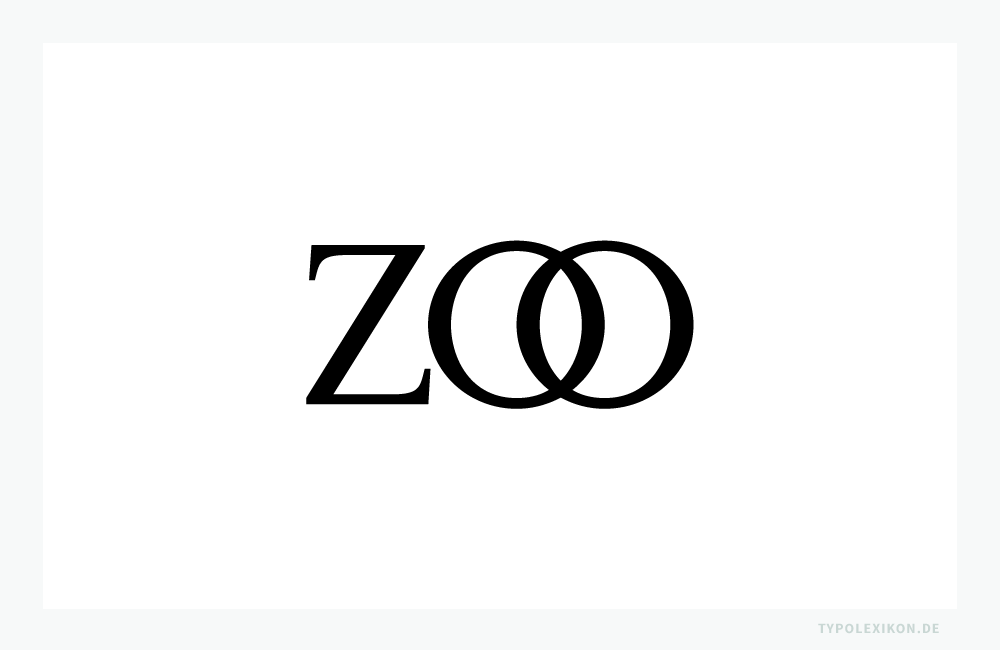
Eine Ligatur verfügt immer über einen natürlichen Breitenlauf bzw. eine feste Normalschriftweite (NSW 0) und kann somit im Sinne des Optischen Schriftweitenausgleichs auch nicht spationiert, unterschnitten oder ausgemittelt werden.
Die Verwendung von Ligaturen ist in keiner europäischen Sprache orthografisch vorgeschrieben. Grundsätzlich sind Ligaturen bei allen Druckschriften und Screen Fonts römischen Ursprungs kein notwendiger Bestandteil des Schriftsystems.
Die deutschen Orthographie kennt – abgesehen vom »ß« (Eszett, Scharfes s), das es heute nur noch in der deutschen Sprache gibt – keine Ligaturen, wobei streng genommen das »ß« in der deutschen Rechtschreibung als Einzelbuchstabe und nicht als Ligatur wahrgenommen wird und ggf. auch durch »ss« bzw. im Majuskelsatz generell durch »SS« ersetzt werden kann (siehe Eszett). 1) 2) 3) 4) 5) 6)
Die Letternarchitektur, die Anzahl von Ligaturen je Schriftart und deren Gebrauch folgt ausschließlich typografischen Regeln, die je nach geschriebener Sprache, Epoche, Schriftart und Schriftsatzsystem voneinander mehr oder weniger stark abweichen. Verbindliche Regeln, wie Ligaturen gegenwärtig im deutschsprachigen Raum gesetzt werden, existierten nicht.
Abgesehen von »&« (et), 7) »§« (signum separationis) 8) »%« (per cento), »@« (engl. at, siehe @-Zeichen) sowie in Deutschland und Österreich »ß« (Eszett, Scharfes s), sind Ligaturen in Tastaturlayouts von Schreibmaschinen, Textverarbeitungssystemen oder Computerterminals nach der Tastaturbelegung 1 der DIN 2137:2012-06 nicht vorgesehen.
Im Segment der Lesetypografie gelten Ligaturen als lesehemmend, da sie nicht mehr den gegenwärtigen Lesegewohnheiten entsprechen. In der Gebrauchstypografie (Akzidenzsatz) bzw. im Grafikdesign werden sie gerne als Zierligaturen verwendet. Innerhalb von Webanwendungen können Ligaturen ggf. zu Performance-, SEO- 9) und Kompatibilitätsproblem führen.
Ligaturen können nur mit professionellen Desktop Publishing Computerprogrammen, beispielsweise InDesign® von Adobe® oder QuarkXpress® von Quark®, und Fonts (z.B. OpenType Fonts) mit Ligaturen in einen Schriftsatz korrekt eingearbeitet werden. In Textverarbeitungsprogrammen, z.B. Microsoft Word® oder Pages von Apple®, können Standardligaturen zwar im Rahmen der OpenType-Technologie automatisch aktiviert, jedoch nicht fachgerecht verwendet werden.
Ursprung und Historie
Die Epigraphik, die Paläografie und die Diplomatik dokumentieren bereits in vorrömischen Alphabeten erste Zeugnisse von Ligaturen und Abbreviaturen (Abkürzungen). 10) Bis zur Spätantike dienten sie dazu, den Zeilenanfang und das Zeilenende optisch auszugleichen (Optischer Randausgleich). Besonderer Ligaturenreichtum ist bei epigraphischen Schriften festzustellen.
In der Kalligraphie erfüllten Ligaturen primär die Aufgabe, schnell und ökonomisch zu schreiben, da u.a. Trägermaterialien wie Pergament bzw. später Papier sehr rar und kostbar waren. Sprachliche Aspekte, beispielsweise die Entwicklung des Konsonanten »w« aus einer Ligatur von zwei »v« bzw. »u« kamen erst später hinzu (11./12. Jahrhundert). Ästhetische Aspekte in der Formgebung und Anwendung erst nach dem Manierismus. Generell ist es sehr schwer festzustellen, ob und ab wann eine Ligatur als originär oder als zusammengesetzt betrachtet werden muss.
In der europäischen Kalligraphie werden Ligaturen spätestens seit dem 1. Jahrhundert – z.B. in Form des Et-Zeichens (lt. »et« für »und«) – genutzt. Zu den ältesten noch angewandten Wortligaturen zählt das Et-Zeichen aus dem Zeichenrepertoire der Tironischen Noten von Marcus Tullius Tiro (um 103–4 v.Chr.), welches auch heute noch in Irland in unveränderter Form genutzt wird.
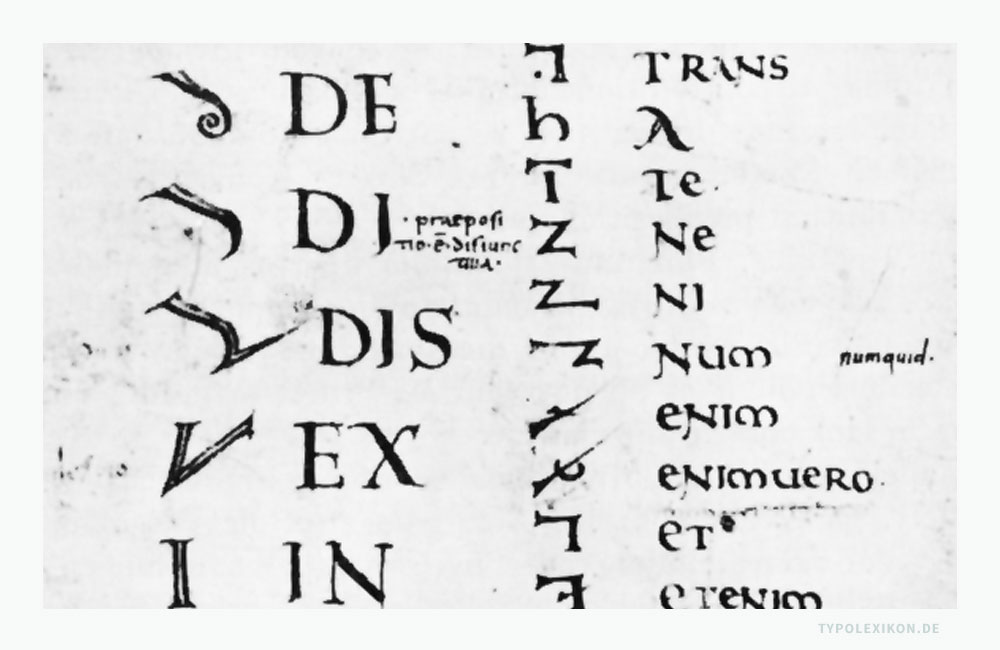
Der Prototypograf Johannes Gutenberg (um 1400–1468) übernahm aus der Kalligraphie die Formgebung von Ligaturen und Abbreviaturen. Beispielsweise entwarf und schnitt er 1460 für den Druck der berühmten Mainzer Erstausgabe des aus dem Jahre 1286 stammenden »Catholicon« – ein in lateinischer Sprache verfaßtes etymologisches Wörterbuch und einer Grammatik zur Bibel – des Dominikanerpaters Johannes Balbus (geboren vermutlich in der ersten Hälfte des 13. Jahrhunderts in Genua, gestorben um 1298) eine »Gotico-Antiqua-Type« (Catholicontype) mit 22 Majuskeln, 103 Minuskeln mit und ohne Abbreviaturen, 81 Ligaturen und vier Sonderzeichen. Insbesondere die Ligaturen nutzte Gutenberg, um in zwei Kolumnen zu jeweils 66 Zeilen platzsparend drucken zu können.
Ligaturen wurden im deutschsprachigen Werksatz von Offizinen rund 500 Jahre lang bis zum Ende des materiellen Schriftsatzes (Bleisatz) verwendet; in der BRD, Österreich und der Schweiz bis Mitte der 1980er bzw. in der DDR teilweise bis nach der deutschen Wiedervereinigung (1989/1990), u.a. von der Offizin Andersen Nexö in Leipzig. 11)
Ab den 1960er Jahren mit der sukzessiven Einführung des Fotosatzes (optomechanischer Schriftsatz) und dem damit einhergehenden Verzicht der Buch- und Zeitungsverlage auf die Verwendung von typografischen Ligaturen – dies war nun technisch möglich und deutlich günstiger –, veränderten sich auch die Lese- und Betrachtungsgewohnheiten der deutschlesenden Rezipienten.
Spätestens ab Mitte der 1980er Jahre sind typografische Ligaturen in Deutschland, Österreich und der Schweiz nicht mehr gebräuchlich.
Arten von Ligaturen
Bei Druckschriften und Screen Fonts römischen Ursprungs gibt es unterschiedliche Arten von Ligaturen:
- Kaufmannsligaturen, z.B. das Prozentzeichen »%«
- Tonligaturen
– Phonetische Majuskelligaturen, z.B. »Æ«
– Phonetische Minuskelligaturen, z.B. das Eszett »ß« - Typografische Ligaturen
– Minuskelligaturen zweifach, z.B. für »fi«
– Minuskelligaturen dreifach, z.B. für »ffi«
– Majuskelligaturen zweifach, z.B. für »TT«
– Majuskelligaturen dreifach, z.B. für »THE« - Unterschneidungsligaturen (siehe Unterschneiden)
- Wortligaturen, z.B. »&«
Im deutschsprachigen Raum werden heute nur noch die Tonligatur »ß« (Eszett), 12) die Wortligaturen »&« (et) und »§« (signum separationis) 13) sowie die Kaufmannsligaturen (ligatura mercatoris) »%« (per cento) und »@« (engl. at) verwendet.
Im Hochdeutschen ist der Schriftsatz, abgesehen von »ß«, frei von Ligaturen, wobei wie bereits erwähnt, das »ß« aus Sicht der deutschen Orthographie als Sonderzeichen wahrgenommen wird, nicht als Ligatur.
Gründe für die Verwendungen von Ligaturen
Im materiellen Schriftsatz werden Ligaturen aus folgenden Gründen verwendet:
- als Ersatz für manuelle Unterschneidungen, die im Blei- und Holzsatz sehr aufwendig und materialintensiv sind
- als Lesehilfe zur Verdeutlichung von Wortfugen
- als platzsparende Abbreviaturen
- als Zierligaturen (Schmuckligaturen)
- um bei bestimmten Buchstabenkombinationen kritische Vor- und Nachbreiten zu vermeiden, die einen ungleichmäßigen Grauwert zu Lasten der Lesbarkeit und der Ästhetik ergeben könnten
- um die Aussprache eines Lauts zu verändern
- um einen Formsatz zu erzwingen
- um im Werksatz im natürlichen Breitenlauf (Normalschriftweite) platzsparend zu setzen
Und im DTP Desktop Publishing: 14)
- als platzsparende Abbreviaturen
- als Zierligaturen
- bei deutschem Fraktursatz
- um die Aussprache eines Lauts zu verändern
Ligaturen im deutschsprachigen Bleisatz
Grundsätzlich ist festzustellen, dass die Fraktur über 400 Jahre die Buch- und Verkehrsschrift der Deutschen und Österreicher und bis 1941 die offizielle Amtsschrift im Deutschen Reich war. Der deutsche Typograf und Schriftgelehrte Jan Tschichold (1902–1974) bemerkte: 15)
Wie kommt es, dass die alten Antiquaschriften vor der Mitte des 19. Jahrhunderts kein ß enthalten? Es war bis gegen 1800 gar nicht, später nur selten üblich, Deutsch in der Antiqua zu setzten …
Der Gebrauch von Ligaturen im deutschsprachigen Raum konzentriert sich deshalb überwiegend auf die der Gebrochenen Schriften. Daraus ergeben sich – im Vergleich zur Französischen oder Englischen Typografie – eigenständige Gesetzmäßigkeiten in Form, Aussprache und Anwendung von Ligaturen beim Satz Gebrochener Schriften.
Der ausschließliche Gebrauch von Antiqua-Schriften in der deutschen Sprache während des materiellen Schriftsatzes beschränkt sich in Deutschland und Österreich auf rund 40 bis maximal 50 Jahre – von ungefähr Mitte der 1940er bis Ende der 1980er Jahre.
Minuskelligaturen im deutschsprachigen Bleisatz
Minuskelligaturen für Werksatzschriften wurden bzw. werden auf einem Schriftkegel im natürlichen Breitenlauf geschnitten. Bei der Fraktur sind die Zweifachligaturen ch, ck ff, fi, fl, ft, ll, fch, ∫i, ∫∫, ß, ∫t, tt und tz sowie die Dreifachligatur fch geläufig. Sie galten im Fraktursatz als unabdingbar (korrekte Formgebung der Frakturligaturen siehe Abbildung ↓ der Schriftprobe »Wilhelm-Klingspor-Schrift«). Der Typograf Albert Kapr (1918–1995) beschrieb ihre Wichtigkeit folgendermaßen: 16)
Eine Quelle der Schluderei beim Satz gebrochener Schriften ist das Mißachten von Ligaturen, die beim nicht gesperrten Satz unbedingt eingesetzt werden müssen, so tz, ß, ∫i, ∫t, ∫i, ff, fl, fi, ll, ch und ck und gelegentlich noch einige andere.
Bei den Antiqua-Schriften waren in Deutschland und Österreich nach dem II. Weltkrieg die Zweifachligaturen für ch, ck, ff, fi, fl, ft, ß und tz sowie selten Dreifachligaturen für ffi und ffl gebräuchlich.
Majuskelligaturen im deutschsprachigen Bleisatz
Da bei Gebrochenen Schriften der Versalsatz nicht üblich ist – die Alternative zum Satz in Großbuchstaben war der Sperrsatz–, kennt die »Deutsche Schrift« folglich auch keine Majuskelligaturen, sondern nur Minuskelligaturen. 17) Phonetische Majuskelligaturen, z.B. »Æ«, gab es überwiegend nur für Antiqua-Schriften im Fremdsprachensatz, äußerst selten bei Fraktur-Schriften, so beispielsweise bei der »Peter-Jessen-Schrift« des Offenbacher Typografen Rudolf Koch (1876–1934), die 1931 bei Schriftgießerei der Gebrüder Klingspor in Offenbach am Main erschien.
Die phonetischen Majuskelligaturen »Æ« und »Œ« (bzw. »æ« und »œ«) wurden von deutschen Handschriftsetzern als Französisches Betonungszeichen (Akzentzeichen) für»Ä« und »Ö« verstanden, nicht als typografische Ligaturen. 18)
Regeln für das Setzten von Ligaturen
Verbindliche Regeln, wie Ligaturen im deutschsprachigen Raum gesetzt werden, existierten heute nicht mehr. Allerdings gibt es gewisse Reglements, die sich aus den »Regeln zur Verwendung von Ligaturen im Fraktursatz« in Relation zur deutschen Rechtschreibung des beginnenden 20. Jahrhunderts rekrutieren.
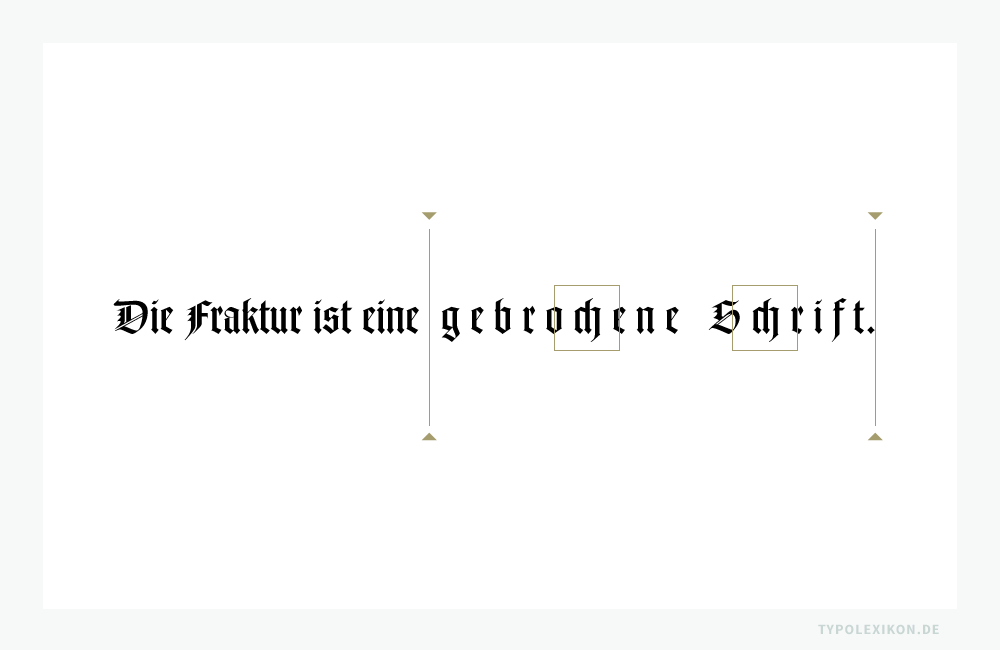
Geläufige Regeln (Auswahl) für den deutschsprachigen Ligaturensatz:
- bei der Spationierung einer Antiqua werden alle Ligaturen aufgelöst
- bei der Worttrennung am Zeilenende werden Ligaturen aufgelöst
- im Sperrsatz einer Fraktur müssen die Ligaturen aufgelöst werden, jedoch nicht ß, tz, ch und ck
- keine Ligaturen für getrennt gesprochenen Buchstaben
- keine Ligaturen im gesperrten Satz
- Ligaturen dürfen am Wortende (Beugungsendungen und Endsilben) nicht getrennt werden, jedoch bei mit einer »i« beginnenden Nachsilben schon
- Ligaturen richten sich nicht nach den Sprachsilben
- Ligaturen sind dort anzuwenden, wo sie die sprachliche Richtigkeit nicht stören
- Ligaturen verbinden keine Wortstämme von Komposita
- Minuskelligaturen im Versalsatz von Antiqua-Schriften sind nicht erlaubt
- ss kann es nicht geben, stattdessen muss eine Ligatur verwendet werden
- treffen drei Buchstaben zusammen, von denen je zwei eine Ligatur bilden können, entscheidet die Silbengrenze
Die Ligatur »Eszett« in der Schweiz
Die Schweiz (und Lichtenstein) bildet in Bezug auf die Ligatur »ß« (Eszett) eine Ausnahme, da deren Kantone zum Ende der 1930er Jahre begannen, das »Scharfe s« in den Primarschulen (Grundschulen) nicht mehr zu lehren. 19) Das althergebrachte Eszett wird seither in der Schweiz mit »ss« aufgelöst, was gemäß der deutschen Orthographie auch in Deutschland und Österreich möglich ist. Offiziell abgeschafft wurde das »ß« in der Schweiz allerdings aber nie.
Ligaturen im digitalen Corporate Publishing
Abgesehen von Ton-, Wort- und Kaufmannsligaturen ist der korrekte Gebrauch von Buchstabenverbindung – z.B. von Bogenligaturen – für den digitalen Mengensatz nicht standardisiert und sehr zeitaufwendig.
Ligaturensatz mit Layout- und Satzprogrammen
Im DTP Desktop Publishing ist es mit professionellen Layout- und Satzprogrammen, beispielsweise InDesign® und Illustrator® von Adobe® oder QuarkXpress® von Quark®, technisch möglich, jegliche Arten von Ligaturen aus einem OpenType Font in einen Schriftsatz einzuarbeiten.
Da professionelle Layout- und Satzprogramme für den internationalen Markt optimiert sind, folgen sie keinen speziellen sprach- und landesspezifischen typografischen Regeln für die Verwendung von Ligaturen. Ein stereotyper Austausch von Buchstabenpaaren (z.B. »fi« oder »ff«) gegen die jeweilig korrespondierenden Standardligaturen ist nach den typografischen Regeln gemeinhin fehlerhaft (siehe obige Regeln für das Setzen von Ligaturen).
Ligaturen bei OpenType Fonts
Seit dem Jahre 1997 ist es durch die OpenType-Fonttechnologie von Adobe® und Microsoft® möglich – ein Font kann technisch betrachtet +/-65.000 Zeichen im Unicode®-Zeichencodierungsstandard umfassen –, Druck- und Screen Fonts mit einer Vielzahl von Ligaturen auszustatten, wobei Unicode® nur für rund 40 Standardligaturen für die Sprachen lateinischen Ursprungs Unterstützung bietet. Das Unicode Consortium lehnt es grundsätzlich ab, weitere Ligaturen in den Unicode® aufzunehmen, da dadurch schwerwiegende Kompatibilitätsprobleme mit bestehenden Zeichenkodierungen entstehen. 20) 21)
Unabhängig davon ist in der digitalen Schriftgestaltung (Type Design) allerdings seit einigen Jahren bei Antiqua-Schriften eine babylonische Vielzahl von Ligaturen zu beobachten, die in ihrer Formvielfalt und Anzahl die der analogen Ära weit übertrifft.
Im Zeichenvorrat (Figurenverzeichnis) eines Fonts, insbesondere von Zierschriften (Decorative), kann es Duzende von fantasievollen Verbundbuchstaben geben. Vereinzelt finden sich bei OTF Fonts auch spezielle Schriftschnitte, deren Zeichenrepertoire ausschließlich aus Ligaturen besteht, beispielsweise die Mrs Eaves Just Ligatures Roman von Zuzana Licko, USA 1995, die u.a. auch Majuskelligaturen für CE, OC, OG, OO, CE, TE THE, TR, TT, TW TY, UR oder VA enthält und den normalen Schriftschnitt der Mrs Eaves ergänzt.
Bei Gebrochenen Schriften in OTF-Formaten dagegen ist das Angebot an Ligaturen sehr begrenzt und für den deutschsprachigen Ligaturensatz in der Regel unvollständig. Darüberhinaus herrscht bei dieser Schriftgattung ein heilloses Tohuwabohu bei der Adressierung (Codierung) der Ligaturen, beispielsweise beim Lang-f.
Wie auch im materiellen Schriftsatz, lassen sich Ligaturen bei OpenType Fonts im Sinne des Optischen Schriftweitenausgleichs nicht sperren, spationieren, unterschneiden oder ausgleichen, was insbesondere bei der Anpassung des Kernings bei Konsultationsgrößen und Ferngrößen sowie im Majuskelsatz sehr nachteilig sein kann. Wird beispielsweise die Normalschriftweite (NSW 0) einer Schrift bei einem kleinen Schriftgrad zur besseren Lesbarkeit erweitert, führt dies zwangsweise zu Problemen bei den Ligaturen.
Typografische Ligaturen in OpenType Fonts sind deshalb heute in erster Linie als Zierligaturen zu verstehen, wobei sehr qualifizierte Typografen:innen damit auch im Segment der Lesetypografie einen Schriftsatz durchaus ästhetisch aufwerten können. Dies erfordert allerdings sehr viel typografisches Fachwissen und ein sehr feines Gespür für Sprache und Typometrie. 22)
Ligaturen bei Webfonts
Wie bei OpenType Fonts ist es auch bei Webfonts technisch möglich, Antiqua-Ligaturen als Sonderzeichen in den Zeichenvorrat einer Schrift einzubinden, um diese dann beispielsweise in einen HTML-Text einzuarbeiten. Allerdings ist der Aufwand für den Typografen:in hier spürbar größer als mit professionellen DTP-Layout- und Satzprogrammen, da HTML-Editoren (z.B. Adobe Dreamweaver®) oder Webanwendungen (z.B. WordPress® oder TYPO3®) nicht für den mikrotypografischen Feinsatz ausgelegt sind. Noch mehr Aufwand erfordert die Verarbeitung von Fraktur-Ligaturen.
Special Features, wie z.B. die Funktion »Webschriftzeichen« beim grafischen HTML-Editor Adobe Muse®, welche die Darstellung von Ligaturen in modernen Browsern sicherstellen soll, sind mit den Regeln des deutschsprachigen Ligaturensatzes inkompatibel, da diese Autofunktionen nur stereotyp gewisse Buchstabenkombinationen (z.B. »ff« oder »fi«) gegen angelsächsische Standardligaturen austauschen, falls diese überhaupt vorhanden sind.
Die meisten aktuellen Clients (z.B. Safari® von Apple® oder Google Chrome® von Google®) können heute OpenType-Features verarbeiten, wobei es allerdings aufgrund systemimmanenter Technologiedefizite oft zu Darstellungsfehlern bei Ligaturen kommen kann, beispielsweise bei einer Abweichung vom Unicode®-Zeichencodierungsstandard oder bei der automatischen Interpretation von Ligaturen im Mozilla Firefox®. Insbesondere bei der Darstellung von deutschen Fraktur-Schriften sind Fehlinterpretationen bei Ligaturen sehr wahrscheinlich.
Ligaturen für Suchmaschinen und Rechtschreibprogramme
Typografische Ligaturen in System- oder Webfonts verhalten sich in aller Regel inkompatibel zu den Algorithmen von Suchmaschinen und Suchfunktionen auf Websites, da diese als Sonderzeichen interpretiert werden. Gleiches gilt für Rechtschreibprogramme, die Ligaturen nicht verifizieren können.
| ↑1 | Quelle: Deutsche Rechtschreibung, Regeln und Wörterverzeichnis, entsprechend den Empfehlungen des Rats für deutsche Rechtschreibung, überarbeitete Fassung des amtlichen Regelwerks 2004 mit den Nachträgen aus dem Bericht 2010. Zum Ersatz von »ß« durch »ss« oder »SS« siehe § 25 E2 und E3. Laut einer Pressemitteilung des Rats vom 29.6.2017 ist in der deutschen Rechtschreibung ab sofort auch – neben SS – eine Majuskelligatur der Minuskelligatur »ß« möglich. Online verfügbar unter www.rechtschreibrat.com (30.6.2017). |
| ↑2 | Literaturempfehlung: Tschichold, Jan: Herkunft und Form des ß in der Fraktur und der Antiqua, Fachaufsatz. Eingebunden auch in der Publikation »Schriften 1925–1974«, Brinkmann & Bose, Berlin, Band 1, Seiten 242–244, ISBN 3-922660-37-1. |
| ↑3 | Literaturempfehlung: Tschichold, Jan: Formwandlung der ET-Zeichen. Erstausgabe als Broschüre im Eigenverlag, 1953. Eingebunden auch in der Publikation »Schriften 1925–1974«, Brinkmann & Bose, Berlin, Band 2, Seiten 120–140, ISBN 3-922660-36-3. |
| ↑4 | Anmerkung: Das »ß« (Eszett) wird im Majuskelsatz (Versalsatz) ausschließlich durch zwei Großbuchstaben, also »SS« dargestellt bzw. falls vorhanden durch eine spezielle Majuskelligatur dargestellt. Eine gesmischte Schreibweise, beispielsweise »MAßSYSTEM«, ist nicht zulässig. |
| ↑5 | Tipp: Bei automatischer Konvertierung von Kleinbuchstabenzeilen in Großbuchstabenzeilen bzw. in Kapitälchen ist darauf zu achten, dass die Minuskelligatur »ß« zweimal händisch durch »SS« ersetzt wird. Ansonsten stimmt die Spationierung zwischen den beiden Buchstaben nicht mehr. |
| ↑6 | Anmerkung: Das Deutsche Institut für Normung (DIN) und die Internationale Organisation für Normung (ISO) haben die Minuskelligatur »ß« in den Zeichensätzen ISO-10646 und Unicode 5.1. als Majuskelligatur für »ß« 2008 normiert. Es hat dort den Platz mit der Bezeichnung 1E9E. Die deutschen Rechtschreibregeln sowie die typografischen Regeln sind davon nicht betroffen, es handelt sich ausschließlich um eine Empfehlung. |
| ↑7 | Anmerkung: Obwohl »&« (et) umgangssprachlich auch als Kaufmanns-Und bezeichnet wird, ist es dennoch keine »Kaufmannsligatur« sondern eine »Wortligatur«. |
| ↑8 | Anmerkung: Ob das Paragraphenzeichen »§« für »signum separationis« (lat. Zeichen der Trennung) eine Ligatur, eine Abbreviatur oder gar ein Abschnitts- oder Trennungszeichen war bzw. ist, darüber gehen die Expertenmeinungen auseinander. |
| ↑9 | Anmerkung: SEO ist die Abkürzung für »search engine optimization« und bedeutet Suchmaschinenoptimierung. |
| ↑10 | Literaturempfehlung: Faulmann, Carl: Schriftzeichen und Alphabete aller Zeiten und Völker, Reprint im Augustus Verlag, ISBN 3-8043-0142-8. |
| ↑11 | Anmerkung: Der erste Bildschirmarbeitsplatz BAP 2000 des VEB Typoart Dresden wurde erst 1985 produziert. Offiziell wurden in der DDR Blei-Schriftsetzer:innen bis 1990 ausgebildet. |
| ↑12 | Anmerkung: Tonligaturen sind phonetische Ligaturen und nicht zu verwechseln mit Ligaturen in der Musik. |
| ↑13 | Anmerkung: Ob das Paragraphenzeichen »§« für »signum separationis« (lat. Zeichen der Trennung) eine Ligatur, eine Abbreviatur oder gar ein Abschnitts- oder Trennungszeichen war bzw. ist, darüber gehen die Expertenmeinungen auseinander. |
| ↑14 | Anmerkung: Betrachtungsweisen, dass der Einsatz von Minuskelligaturen im Segment der Lesetypografie auch heute noch elementar für einen guten Schriftsatz sei, ist pure Setzer-Romantik. Denn satztechnisch gesehen sind Ligaturen für professionelle Desktop Publishing Computerprogramme, beispielsweise InDesign® von Adobe® oder QuarkXpress® von Quark®, nicht mehr notwendig. Darüber hinaus entsprechen Ligaturen auch nicht mehr den heutigen Lesegewohnheiten. |
| ↑15 | Quelle: Tschichold, Jan: Herkunft und Form des ß in der Fraktur und der Antiqua, Fachaufsatz. Eingebunden auch in der Publikation »Schriften 1925–1974«, Brinkmann & Bose, Berlin, Band 1, Seite 242, ISBN 3-922660-37-1. |
| ↑16 | Quelle und Literaturempfehlung: Kapr, Albert: Fraktur. Form und Geschichte der gebrochenen Schriften, Verlag Hermann Schmidt, Mainz, 1993, Seite 95. ISBN 3-87439-260-0. |
| ↑17 | Anmerkung: Dies ist auch der Grund dafür, weshalb auch heute noch die Mehrheit aller Antiqua-Schriften keine Majuskelligatur für das deutsche »ß« (Eszett) besitzen. |
| ↑18 | Quelle: Luidl, Philipp: Typografie, Herkunft, Aufbau, Anwendung. Schlütersche Verlagsanstalt und Druckerei, Hannover, 1984, ISBN 3–87706-212–1, Seite 43–44. |
| ↑19 | Anmerkung: Der Kanton Zürich nutzte das »ß« ab dem 1. Januar 1938 nicht mehr. Am 4. November 1974 stellte auch die Neue Zürcher Zeitung (NZZ) als letzte der Schweizer Zeitungen auf »ss« um. Quelle: Peter Müller, SOK, Schweizer Orthographische Konferenz 2017. |
| ↑20 | Anmerkung: Unicode® ist ein internationaler Standard des Unicode Consortiums, in dem langfristig für jedes Sinn tragende Schriftzeichen oder Textelement aller bekannten Schriftkulturen und Zeichensysteme ein digitaler Code festgelegt wird. Online verfügbar unter http://www.unicode.org (5.4.2017). |
| ↑22 | Tipp: Nur sehr geübte Typografen:innen sollten im Segment der Lesetypografie mit Ligaturen setzen. Denn nicht alles was technisch machbar ist, ist auch sinnvoll! |